一年一度的元宵节马上就要来了!佳节将近,你的品牌海报已经准备好了吗?我们为您整理几款适合元宵节海报的商用字体,希望能给您多一些商用字体的选择。
上首元正体每个字中都带有一个弯,使字体显得更具特点,其余笔画利用的直线,使字体方中带圆,笔画粗而平稳,笔形方头方尾是这套字的一大特色,使字体富有视觉冲击力的同时又给整体呈现出规整,稳定的感觉。
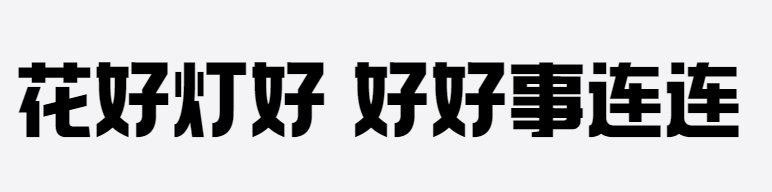
上首元气体字体笔画轻盈,每一笔画都搭配着圆角,显得字体更圆滑可爱。
X-珠圆玉润这款字体是一点都不圆润,该字体字型端正,笔画中既有线条的简洁、硬朗、笔直、流畅明快,也有转折处的婉转优美,能够让读者更快速地阅读,尽显“珠圆玉润”的优雅之感。